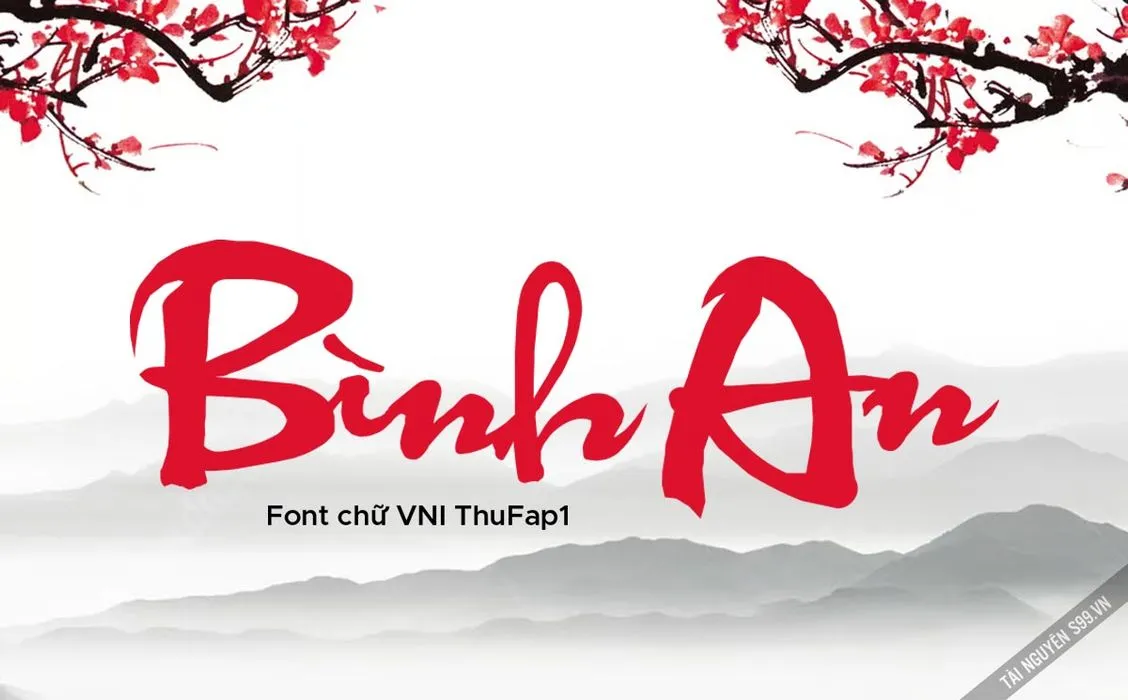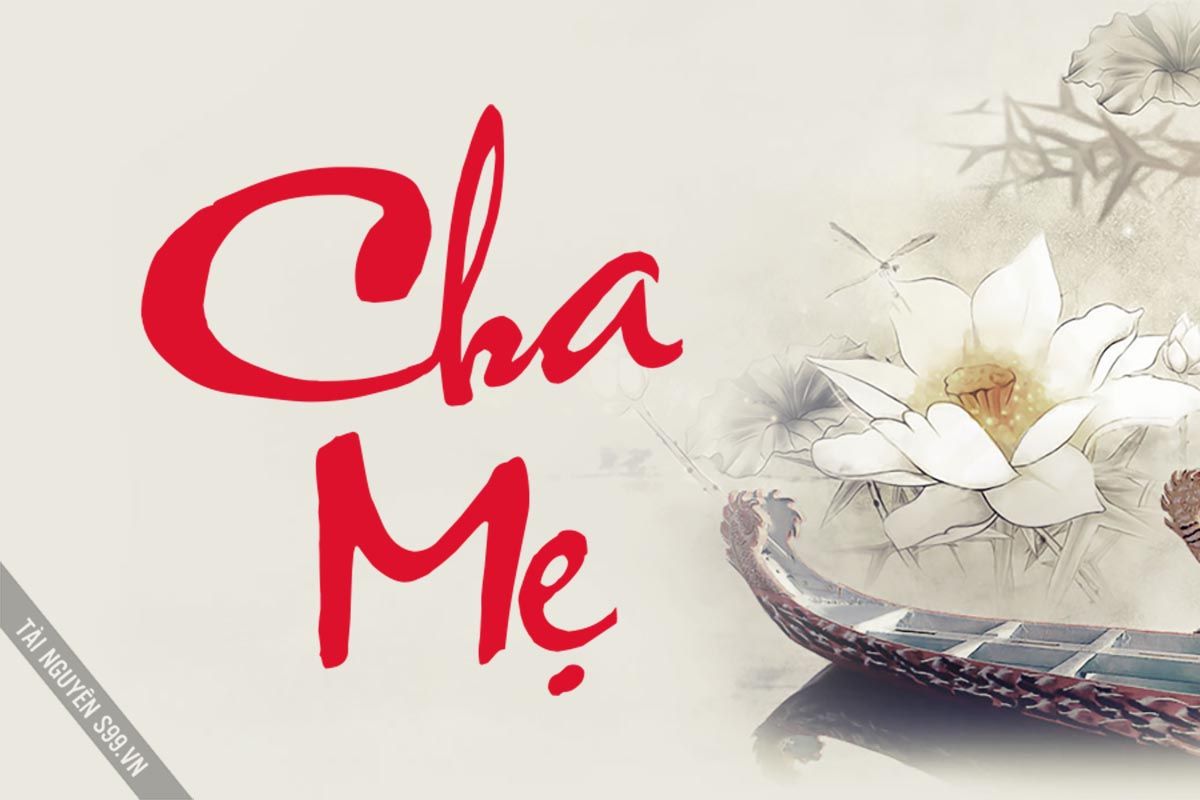
Font chữ VNI ThuFap1 là một trong những font chữ thư pháp đẹp và được nhiều nhà thiết kế ưa chuộng hiện nay. Với phong cách font thư pháp viết tay mềm mại, uyển chuyển, bộ font này mang lại cảm giác truyền thống nhưng vẫn rất hiện đại, phù hợp cho nhiều ý tưởng sáng tạo khác nhau.
Điểm nổi bật của font chữ thư pháp Việt hóa VNI ThuFap1 là hỗ trợ đầy đủ dấu tiếng Việt, đảm bảo tính thẩm mỹ và dễ đọc khi sử dụng trong các thiết kế nội dung văn bản, poster, banner hay ấn phẩm quảng cáo. Đây là lựa chọn lý tưởng cho những ai muốn tạo nên sự ấn tượng trong các sản phẩm văn hóa, nghệ thuật, thiệp cưới, thiệp mời, câu đối Tết hoặc thiết kế mang tính chất truyền thống.
Nếu bạn đang tìm một font chữ thư pháp Việt hóa đẹp, đầy đủ dấu, dễ sử dụng và mang đậm tính nghệ thuật, thì VNI ThuFap1 chắc chắn là lựa chọn không thể bỏ qua.